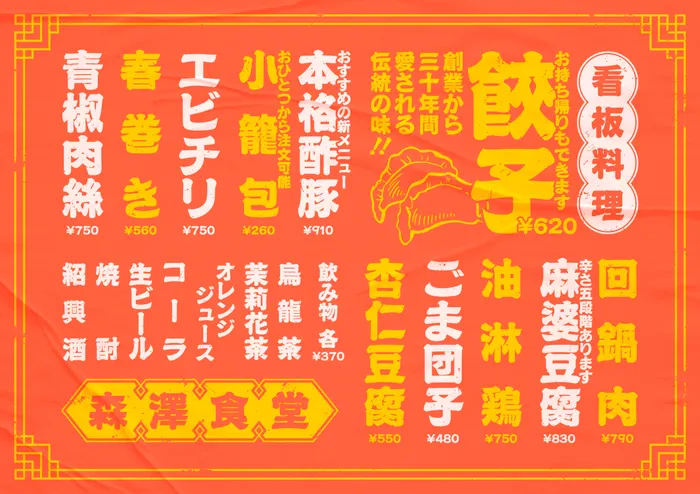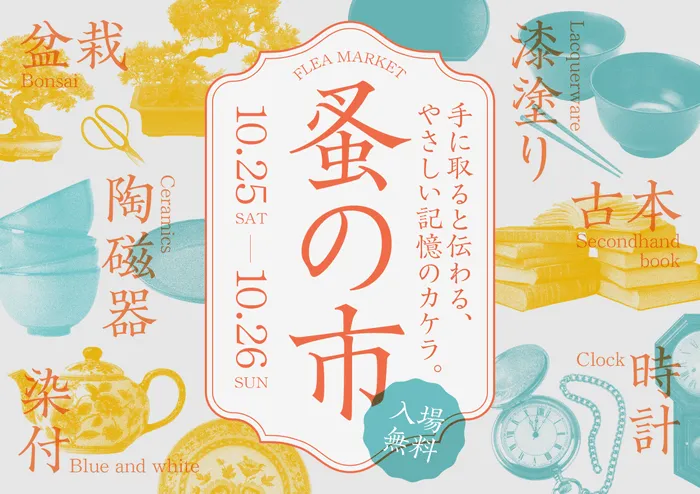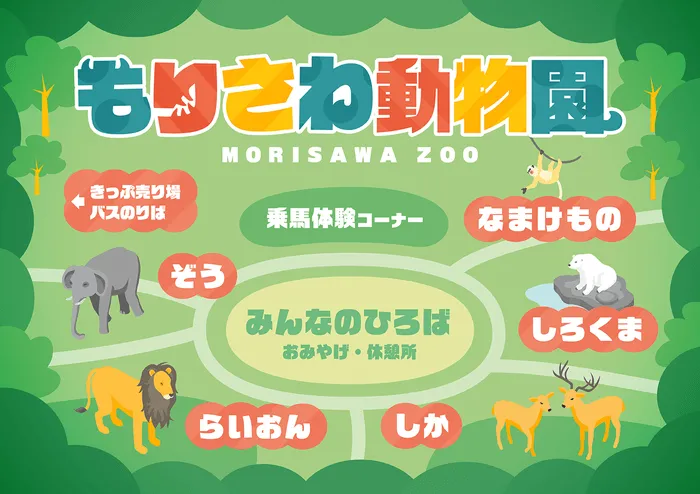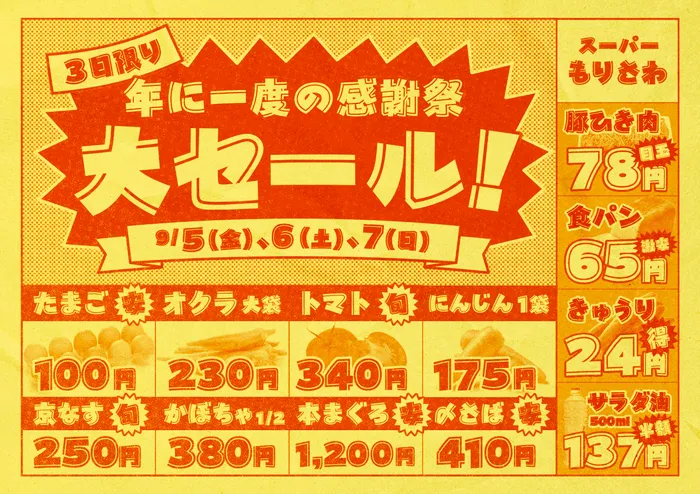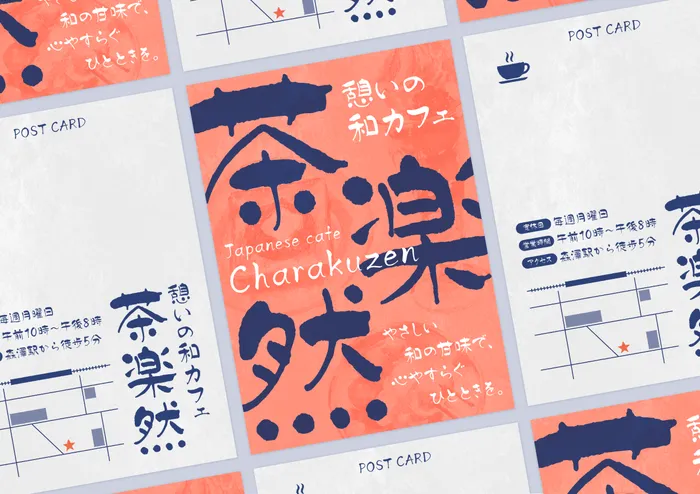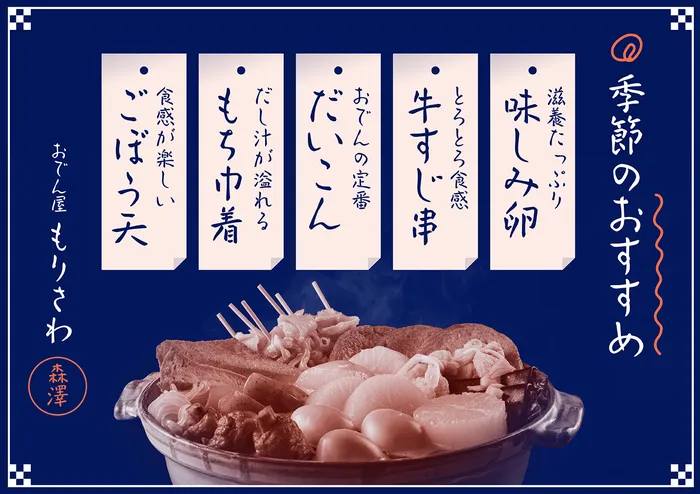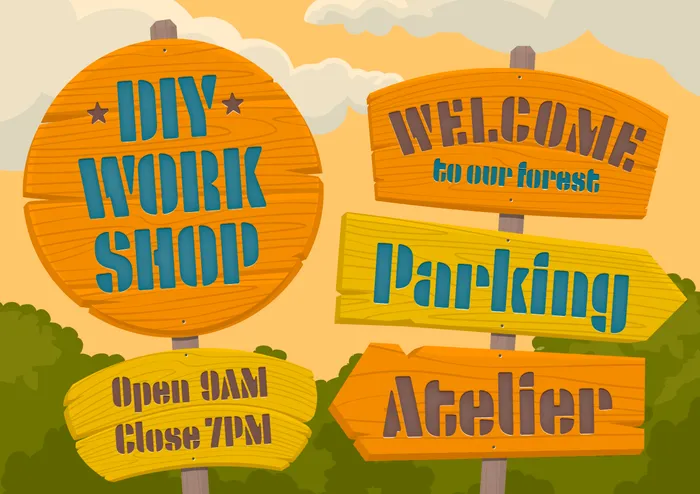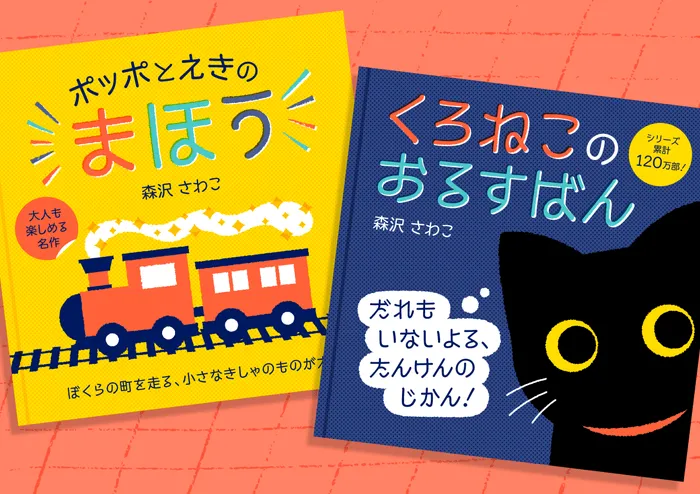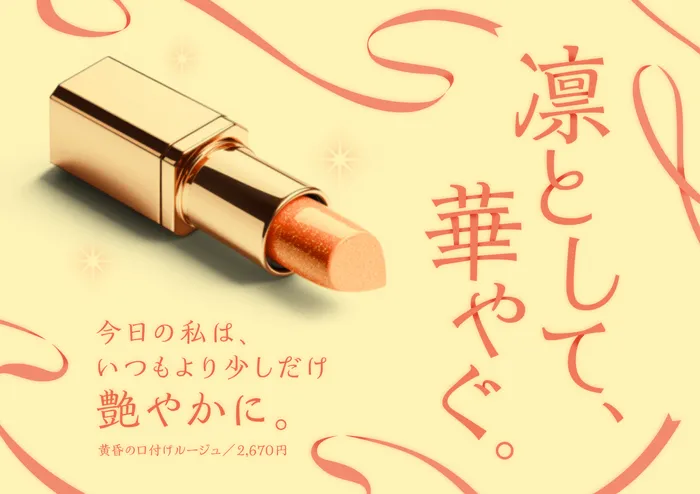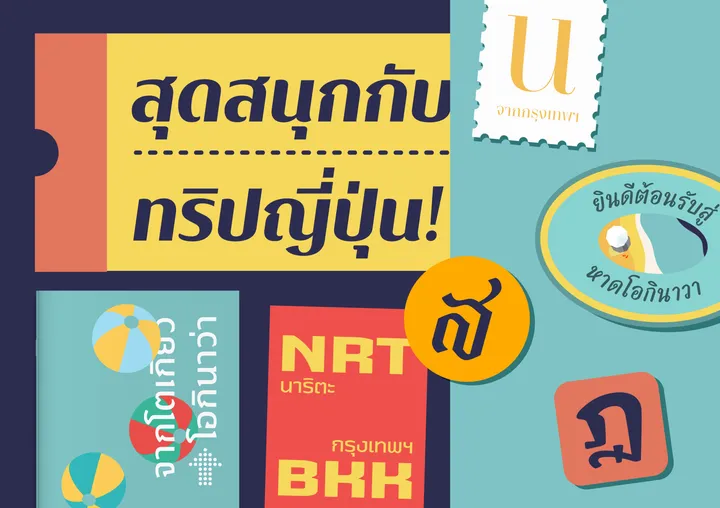
デザインに寄り添う、
懐かしさと新しさ。
毎日のフォント使いの
ヒントになる、
デザインレシピを
公開します!
デザインに寄り添う、懐かしさと新しさ。
毎日のフォント使いのヒントになる、
デザインレシピを公開します!
長年愛される書体から表現に新たなひらめきを与える書体まで、
時代や言語の枠を超えた多彩なラインナップをご提供します。
このサイトでは、書体の特徴に加えて、文字の効果的な使い方やTipsをご紹介。
伝えたいメッセージをさらに引き立てるヒントとして、ぜひご覧ください。
ひとさじのスパイスで味変を
デザインにもう一捻り加えたい時に。入れ過ぎにはご注意を!
ふんわり香るノスタルジックな余韻
優雅さやハイカラな雰囲気が欲しい時はこちら
一層引き立つしっとり深みのある味わい
デザイン全体を、重厚な印象で包み込むならこの書体
「あの頃」と「今」の絶妙なマリアージュ
懐かしい、でも最先端なデザインに合わせて、こんな書体はいかが?